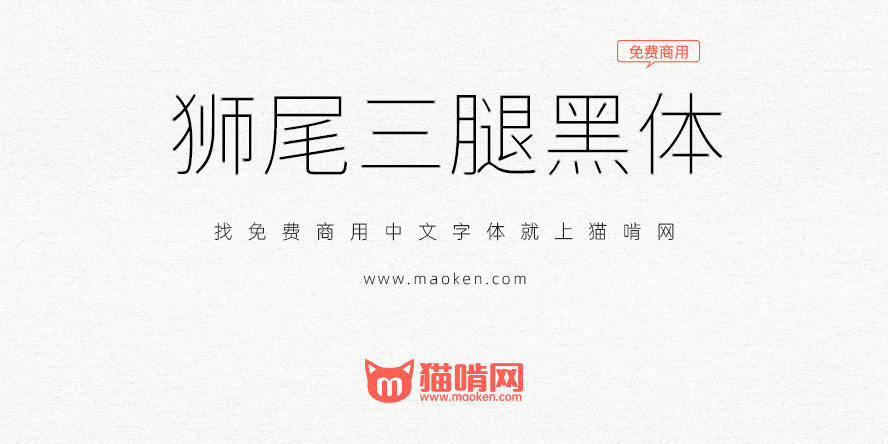
字体作者:Max(中国台湾) | 字体字重:7个 |
狮尾三腿黑体是基于思源黑体笔触进行开花改造,更加简明现代化的字体。狮尾三腿黑体的特色是:「一」字的开头和结尾笔触由平头换成开花式的三个三角形。
狮尾三腿黑体和狮尾三角黑体差别在有没有拔脚,“拔脚”就是会有较少的笔画,例如移除“口”字的左右下角会多出的短线条。有拔脚的字会较圆,但是会造成有些字因直接去掉腿后左右不平衡、左右不对称的“悬空”问题。改使用「腿」系列字体就不会有这个问题。